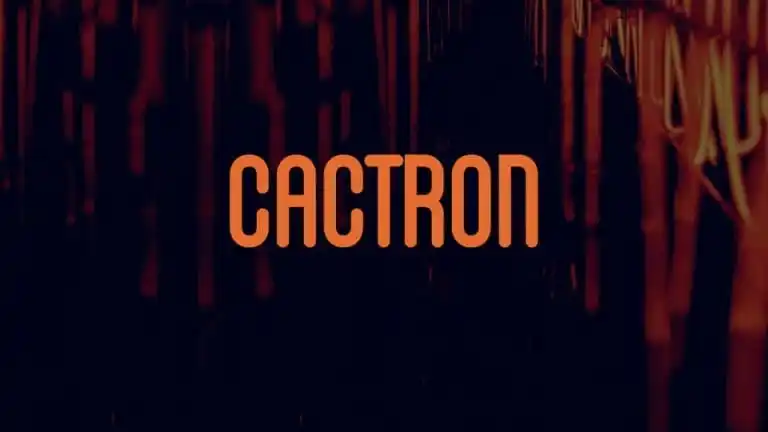
Cactron Sans Serif Font
A Cactron Sans Serif é uma fonte sans-serif que combina uma expressividade autêntica com formas geométricas contemporâneas. Inspirada nas noites urbanas e nas luzes neon, ela celebra a beleza eclética das formas abstratas, apresentando-se de maneira impressionante em diversos ambientes estilizados. Desenvolvida por Na cahua na plataforma 99designs, esta fonte familiares em quatro estilos é uma viagem visual para quem procura um pouco de modernidade e sofisticação em seu trabalho. Com seus ângulos predominantemente curvos e uma consistência ótima nas linhas, a Cactron Sans Serif oferece flexibilidade para adaptar à sua necessidade criativa. Seja você um designer de interface de usuário, editor de conteúdo ou artista gráfico, ela certamente trará um toque único a seu projeto, deixando-o impecável e imprimindo uma identidade distintiva.